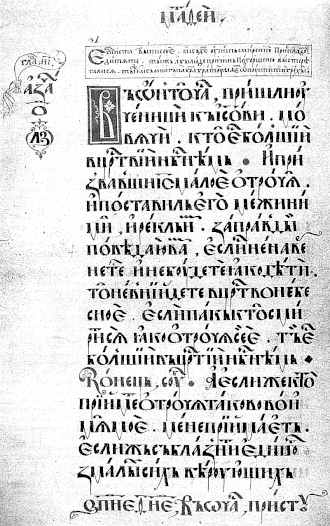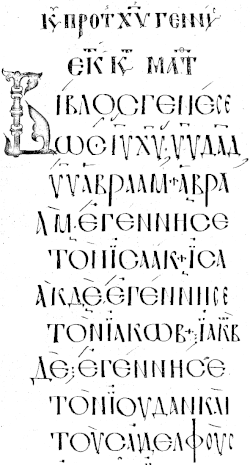
Устав (шрифт)
Уста́в или уставное письмо — почерк с чётким угловато-геометрическим рисунком, при котором буквы пишутся в строке, без наклона, практически вписываются в квадрат, с малым числом выступающих вниз и вверх элементов и большей частью раздельно друг от друга[1]. Медленное и торжественное письмо тщательного каллиграфического исполнения, с малым числом сокращений. В русском языке этот термин применяется к различным письменностям:
- к кириллице (чаще всего) и к глаголице;
- к греческому почерку византийских времен;
- иногда и в других случаях: например, могут упоминать и противопоставлять скорописные японские иероглифы и уставные.
В палеографическом значении термин «устав» употребляется с XIX века, первоначально только по отношению к кириллице. Название связано со сферой применения этого письма: в «высокой» церковной литературе «ѹставьнымъ словѣньскимъ ѩꙁꙑкомъ».
Греческий устав
Греческий устав (в другой терминологии — младший унциал) — маюскульный (одними заглавными буквами) почерк середины I — начала II тысячелетия н. э., первоначально наклонный, но к X веку выпрямившийся. На его основе были созданы готское письмо и кириллица.
Греческий устав обычно выделяется в отдельную категорию в русской терминологии[2], хотя часто его объединяют с унциальным письмом более древнего периода. В некоторых европейских языках устав и унциал (равно как полуустав и полуунциал) вообще называют одним и тем же словом.
Кирилловский устав
Устав — древнейшая форма кириллицы, характерная для древнейших рукописей. Первоначальный кирилловский устав в точности повторял начертания унциального (уставного) письма греческих литургических книг того же времени (IX—XI вв.) — в частности, среди древнейших памятников встречается такое же наклонное начертание букв, как и в византийском уставе[3]. Позже кирилловский устав эволюционировал самостоятельно.
Некоторые древнейшие памятники уставного письма (на пергаменте):
- восточнославянские:
- Остромирово Евангелие (1056—57);
- Архангельское Евангелие (ок. 1092);
- Мстиславово Евангелие (1103—17);
- Юрьевское Евангелие (1119—28);
- Мстиславова грамота (ок. 1130);
- южнославянские (Болга́рия):
- Супрасльская рукопись (X век);[4][5]
- Енинский Апостол (X - XI век);
- Саввина книга (XI век).
В древнем уставе пропорции букв приближались к квадрату (со временем заменявшемуся вытянутым вверх прямоугольником)[6], разделение текста на слова отсутствовало. Различают древний собственно устав (до XIV века) и новый устав — с XV по XVII век (по преимуществу на бумаге; впрочем, не все авторы согласны с такой терминологией — некоторые считают новый устав разновидностью полуустава[7]).
Уставное письмо довольно рано начало переходить в более беглые почерки: появляется наклон, учащаются выступающие за пределы строки части букв, развивается система сокращений. На смену уставу приходит полуустав (иногда выделяют также переходные виды почерка: маюскульный курсив, переходную скоропись и др.[8]).
Как типографский шрифт устав использовался (и используется) только в ученой литературе, тогда как церковная традиционно применяет полуустав. Известно издание Остромирова евангелия, набранное в 1843 году специально изготовленным шрифтом, имитирующим почерк рукописи. В публикациях древнейших памятников письменности с конца XIX века и до конца эпохи металлического набора часто применялся характерный мелкий уставный кириллический шрифт с очень тонкими горизонтальными линиями (которые в репринтах часто не пропечатываются, и в результате буквы И/Н/П или Е/С приходится различать только по контексту). В настоящее время разработано довольно много компьютерных уставных гарнитур, воспроизводящих почерки разных мест и времен. Типографские варианты устава обычно различают прописные и строчные буквы.
Глаголический устав
В глаголице к уставу относят как древнейшие почерки (Киевские листки), так и образцы поздней хорватской угловатой глаголицы, в том числе и типографской.